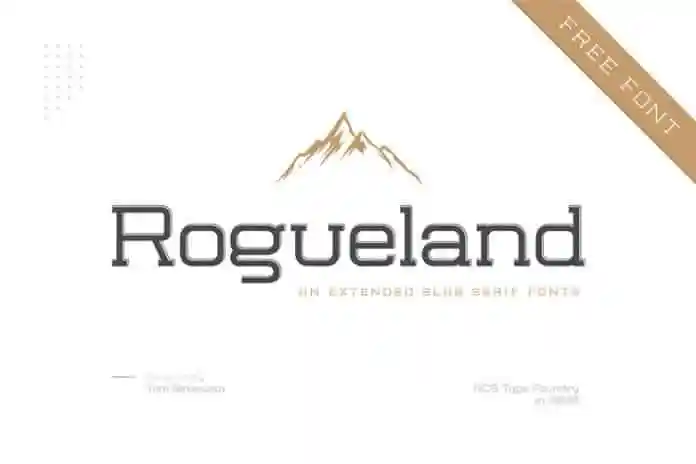
Rogueland Slab Free Font – Download Grátis
Rogueland Slab Free Font é uma fonte de tipo serif slab que traz elementos modernos inspirados no famoso logotipo minimalista. Este tipo de letra está ideal para projetos como templates, brochuras e até mesmo vídeos promocionais, branding e criação de logos. Com recursos que incluem letras maiúsculas e minúsculas, pontuação, números, símbolos e suporte multilíngue, é perfeito tanto para trabalhos tradicionais quanto para projetos digitais. O objetivo da fonte era capturar a essência de um texto com sua personalidade audaciosa, elegância sofisticada e uma aura científica única. Em termos de uso, Rogueland Slab Free Font é uma excelente escolha para qualquer projeto que requer uma tipografia poderosa e elegante.